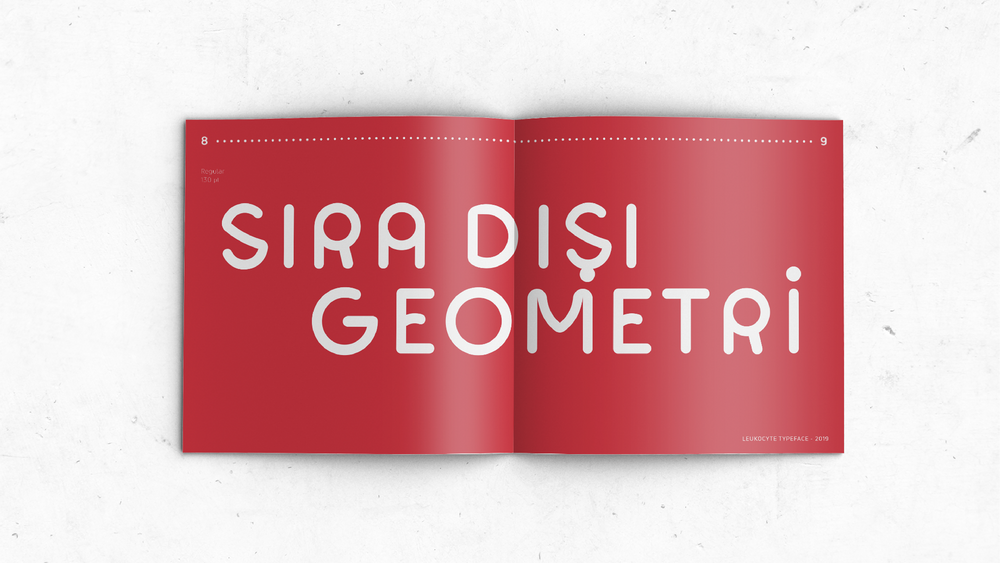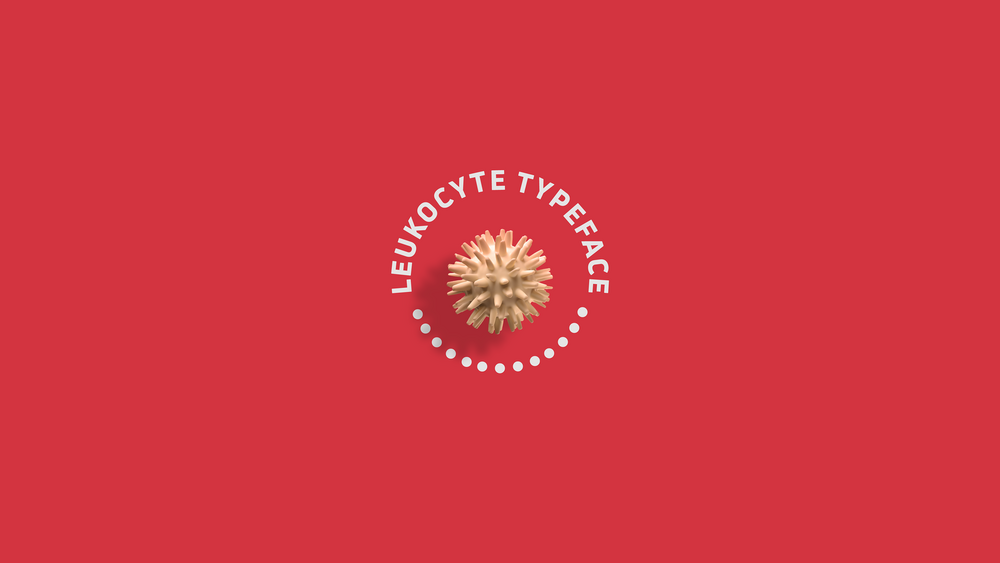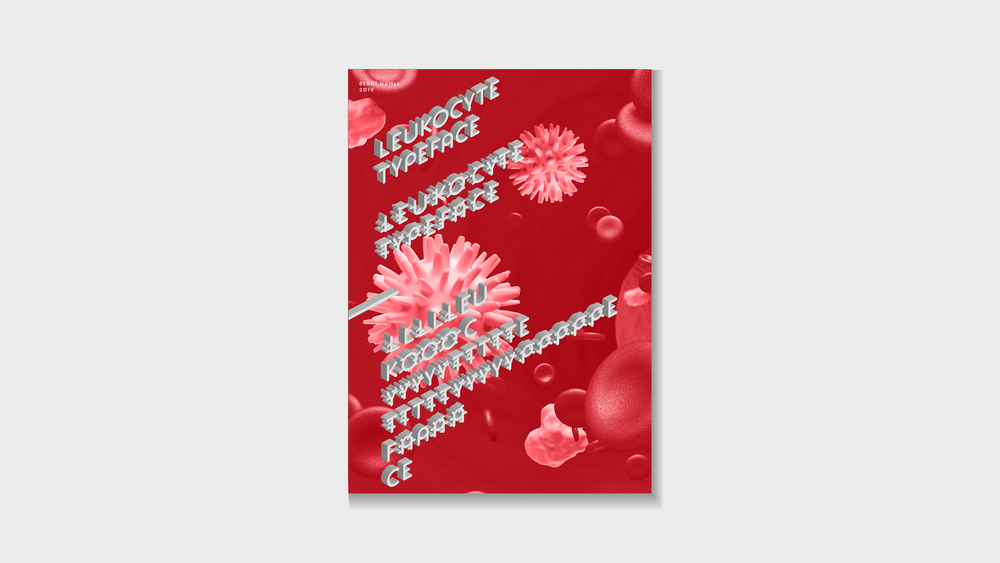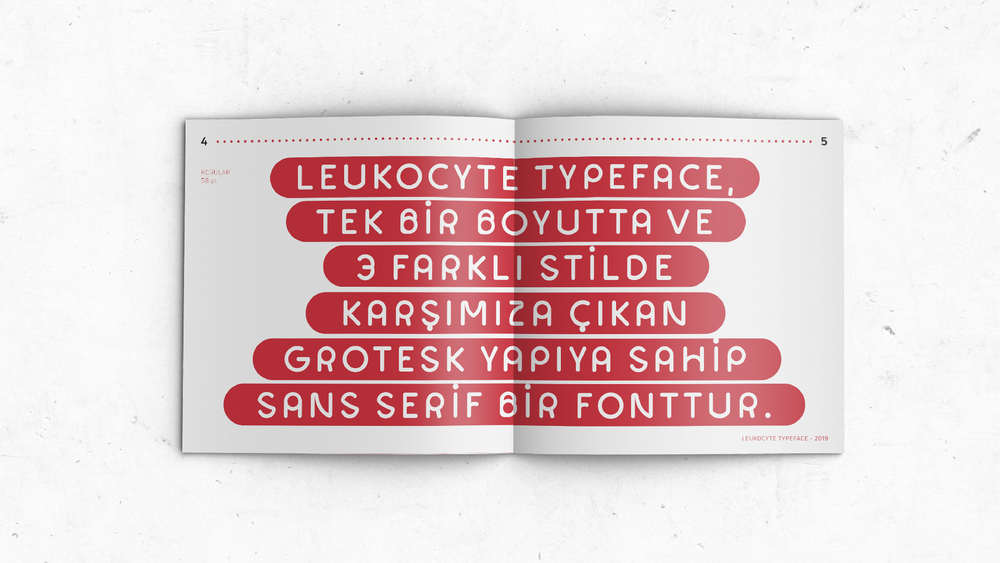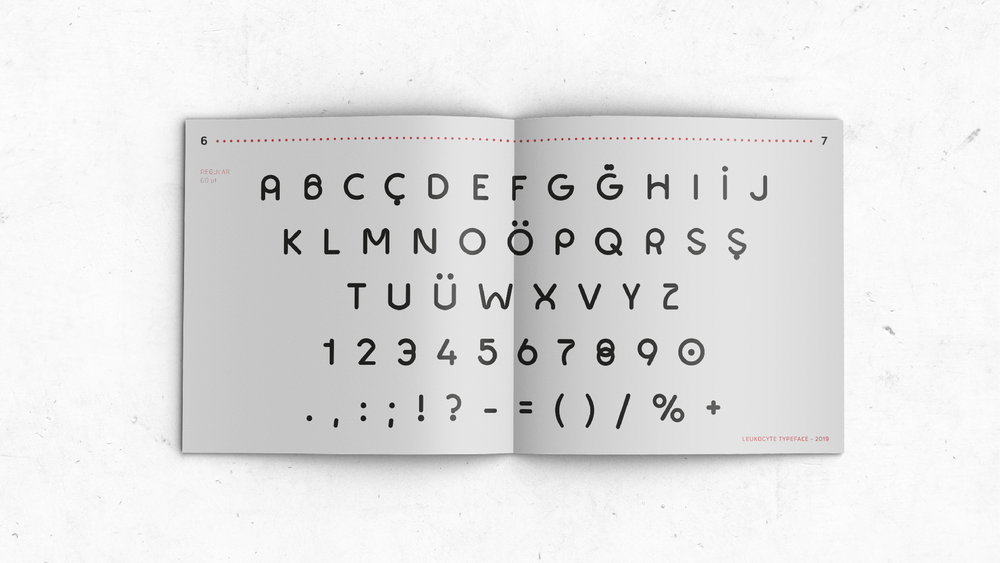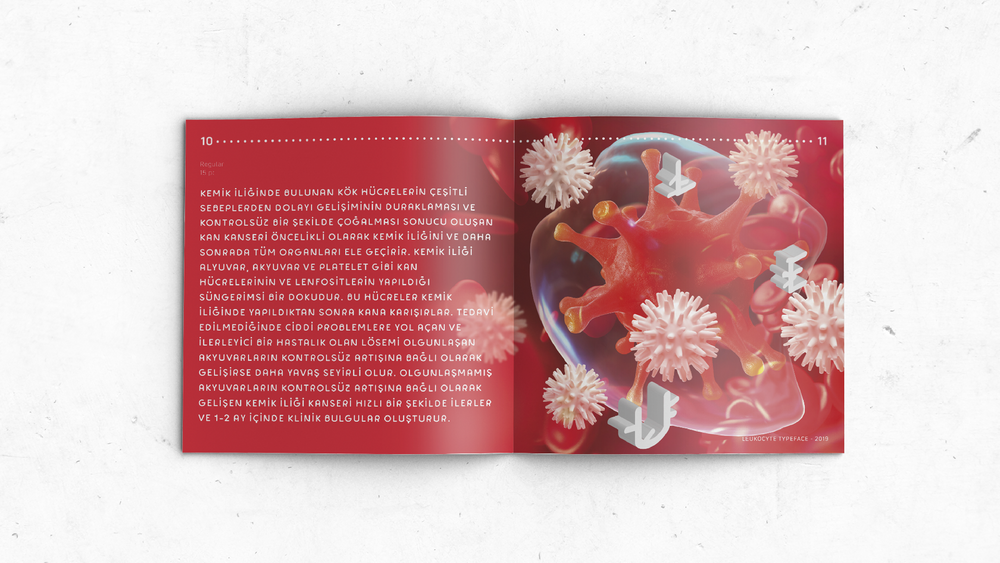
Kontrolsüz çoğalan kan hücrelerinden tipografiye “Leukocyte Typeface”
İzmirli grafik tasarımcı Berat Namlı, Leukocyte Typeface projesini geçtiğimiz yaz ayında paylaşmış. Projenin amacı lösemiye (kan kanseri) dikkat çekmek. Lösemi, kan hücrelerinin özellikle de akyuvarların normalin üzerinde çoğalması ile kendini gösteren bir kanser türü. Dolayısıyla Namlı projesini, akyuvarların (beyaz kan hücreleri) kontrolsüz çoğalmasını ve seyrini gösteren bir deneysel tipografi çalışması olarak tarif ediyor.
Projede; Regular, Display ve News olmak üzere 3 farklı yazıyüzü ailesi bulunuyor. Berat Namlı, Leukocyte Typeface için bir specimen book (örnek kitap) da hazırlamış.